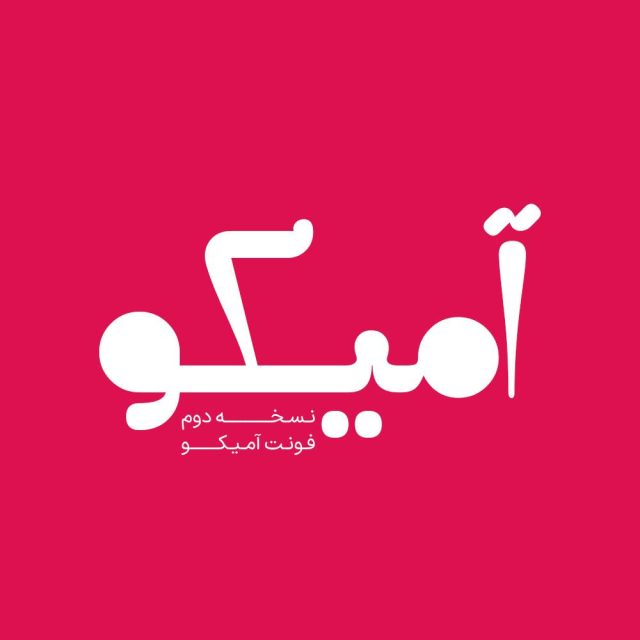
فونت فارسی آمیکو نسخه دو Amico Font
فونت فارسی آمیکو یکی دیگر از فونت های طراحی لوگوتایپ و تایپوگرافی می باشد، فونت آمیکو حرفه ای و انعطاف پذیر می باشد و این امکان را فراهم می آورد که به راحتی بتوانید حروف را در کنار هم قرار دهید، با خرید فونت می توانید بدون هیچگونه دانشی لوگو تایپ طراحی کرده و تایپوگرافی های زیبایی انجام دهید و از آن کسب درآمد کنید. فونت زیبای آمیکو بهترین گزینه برای استفاده در تیتر روزنامهها، مجلات و کتابها است.
فونت فارسی آمیکو یک فونت تک وزن با کاربرد طراحی لوگوتایپ و طراحی های مختلف همچون کتاب و تولید محتوای متن های کوتاه و عناوین می باشد. این فونت با ساختار حروف خود مناسب استفاده در لوگوهای نوشتاری می باشد. همچنین از این فونت در طراحی تابلوهای چلنیوم هم به دلیل ساختار منحصر به فردش می توانید استفاده کنید. در ادامه برای شما نمونه تایپ های این محصول حرفه ای رو آماده کردیم که میتونید مشاهده کنید.
پیشنمایش و نمونه تایپ های فونت آمیکو